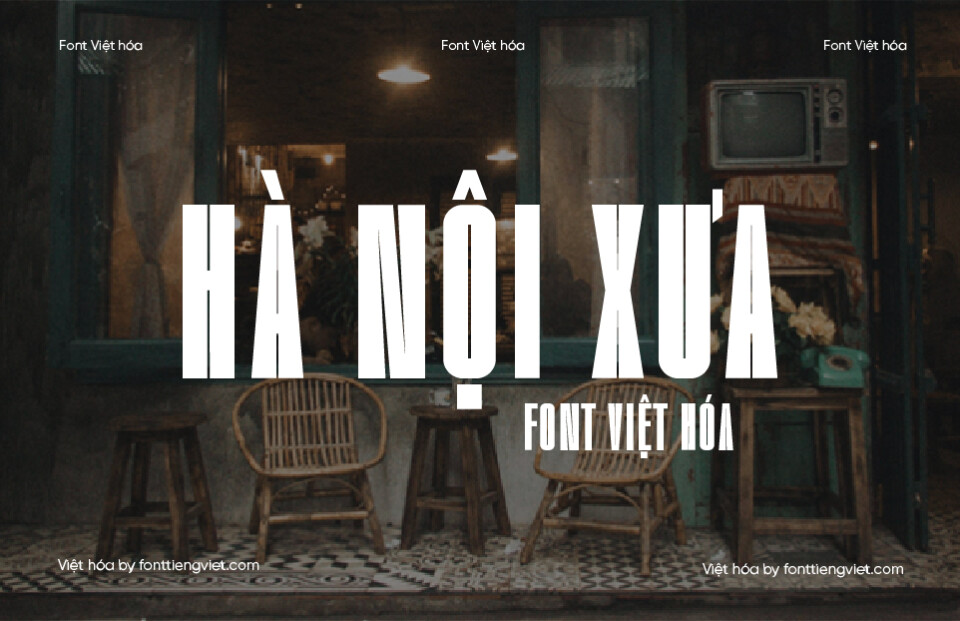
Tải Ngay Font Việt hóa 1FTV VIP Theadzan – Font kiểu xưa Cho Thiết Kế Hoài Cổ
Giới thiệu về Font Việt hóa 1FTV VIP Theadzan – Font kiểu xưa
Trong thế giới đồ họa hiện đại, việc tìm kiếm một bộ Font Chữ mang đậm hơi thở truyền thống nhưng vẫn đảm bảo tính thẩm mỹ cao là điều không hề dễ dàng. Font Việt hóa 1FTV VIP Theadzan – Font kiểu xưa chính là giải pháp hoàn hảo cho những ai yêu thích phong cách Retro và Vintage. Đây là bộ font được tinh chỉnh kỹ lưỡng, giúp các nhà thiết kế dễ dàng tái hiện lại không gian văn hóa Việt Nam những thập niên trước thông qua từng đường nét chữ viết uyển chuyển và tinh tế.
Đặc điểm nổi bật của bộ font kiểu xưa
Bộ font này gây ấn tượng mạnh nhờ cấu trúc chữ thanh mảnh nhưng vẫn giữ được độ chắc chắn cần thiết. Các ký tự được thiết kế dựa trên cảm hứng từ các bảng hiệu vẽ tay cũ tại Sài Gòn và Hà Nội xưa. Điều này giúp Font Việt hóa 1FTV VIP Theadzan – Font kiểu xưa không chỉ đơn thuần là công cụ soạn thảo, mà còn là một tác phẩm nghệ thuật giúp truyền tải cảm xúc và câu chuyện lịch sử vào trong mỗi sản phẩm thiết kế của bạn.
Ứng dụng Font Việt hóa 1FTV VIP Theadzan – Font kiểu xưa vào thực tế
Người dùng có thể ứng dụng bộ font này vào nhiều mục đích khác nhau như thiết kế bìa sách, menu quán cà phê phong cách cổ điển, hay các ấn phẩm truyền thông sự kiện văn hóa. Nhờ việc tối ưu hóa bảng mã tiếng Việt, bộ font đảm bảo không bị lỗi dấu, giúp quá trình làm việc trở nên trơn tru và chuyên nghiệp hơn.
Lợi ích khi sử dụng font Việt hóa chuẩn
Việc sử dụng các bộ font đã được Việt hóa giúp bạn tiết kiệm thời gian chỉnh sửa khoảng cách chữ và dấu câu. Font Việt hóa 1FTV VIP Theadzan – Font kiểu xưa mang lại sự đồng nhất cho toàn bộ văn bản, giúp thông điệp của bạn trở nên gần gũi và dễ chạm đến trái tim người xem hơn bao giờ hết.
Kết luận về bộ font hoài cổ
Nếu bạn đang tìm kiếm một làn gió mới mang phong vị cũ cho dự án của mình, đừng bỏ qua Font Miễn Phí, Font Việt Hóa, Font Việt hóa 1FTV VIP Theadzan – Font kiểu xưa. Đây chắc chắn sẽ là mảnh ghép còn thiếu để tạo nên những tác phẩm đồ họa độc đáo và ấn tượng nhất.